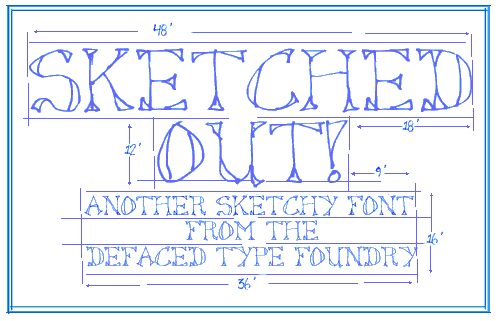
Sketched Out, di S. Roland Frantz, è un carattere display gratuito con grazie, disegnato a mano, dal fascino libero e narrativo. Le lettere appaiono come leggermente abbozzate, con contorni irregolari, giunzioni strette e terminali a cuneo che conferiscono alla struttura serif tradizionale un aspetto filiforme anziché formale.
È perfetto per titoli di poster, copertine di libri, programmi teatrali, packaging e titoli editoriali dove un font gratuito può aggiungere un tocco illustrativo e vagamente vintage, senza risultare datato. Poiché le maiuscole sono strette e ariose anziché massicce, funziona bene anche per titoli, capilettera e monogrammi brevi che richiedono carattere senza troppa pesantezza.